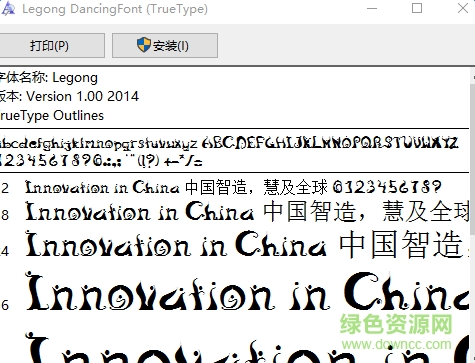
Legong字體是一款很有個(gè)性的電腦英文字體,這款字體寫(xiě)出來(lái)的字是很好看的,而且實(shí)用性強(qiáng),可以用于很多方面,喜歡這款字體的朋友就來(lái)綠色資源網(wǎng)下載吧。
Legong字體確實(shí)是一款很不錯(cuò)的英文字體,字形優(yōu)美,有著自己獨(dú)特的魅力,歡迎有需要的朋友來(lái)綠色資源網(wǎng)下載。